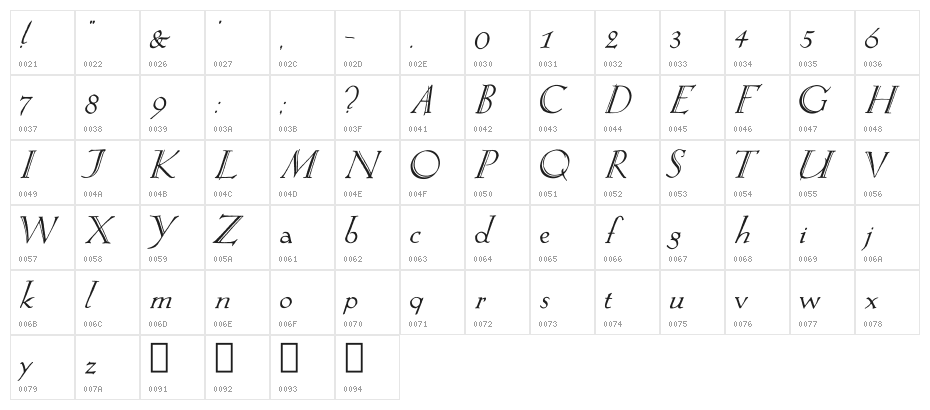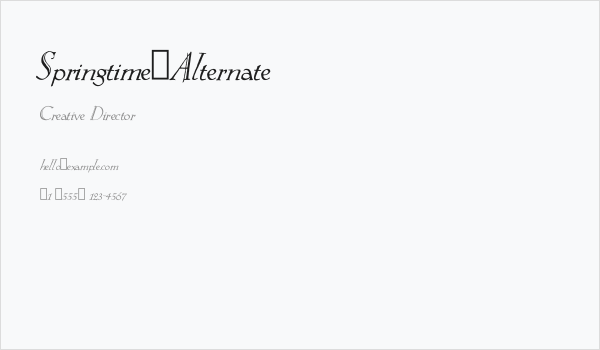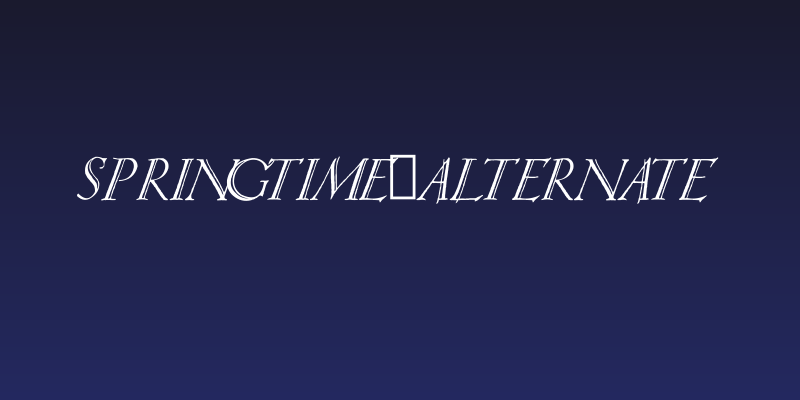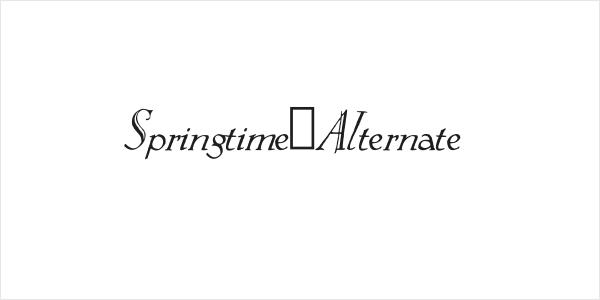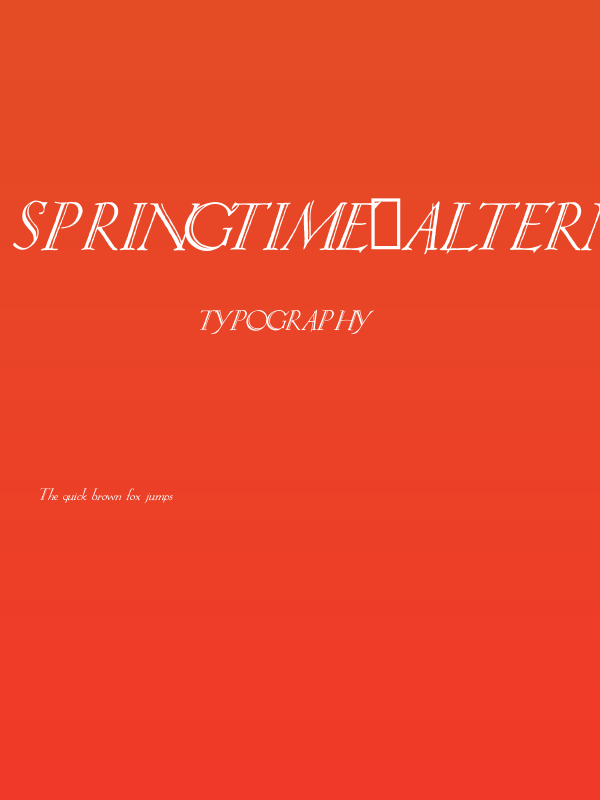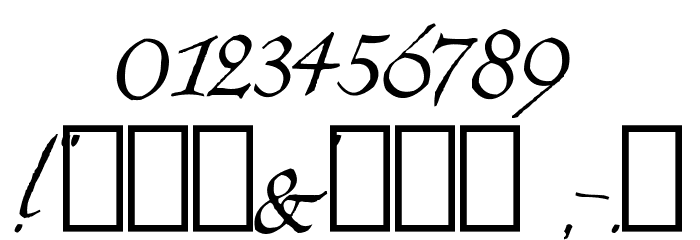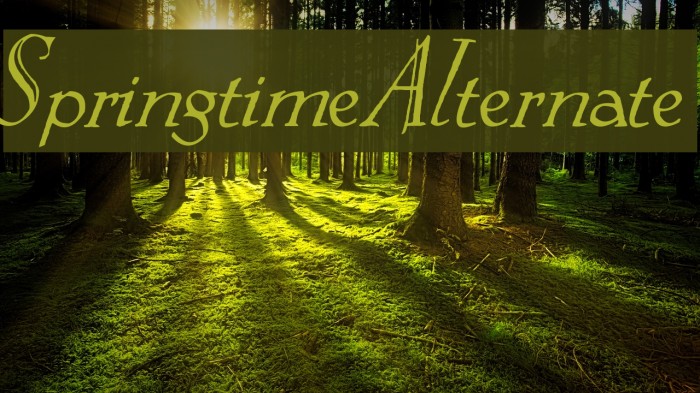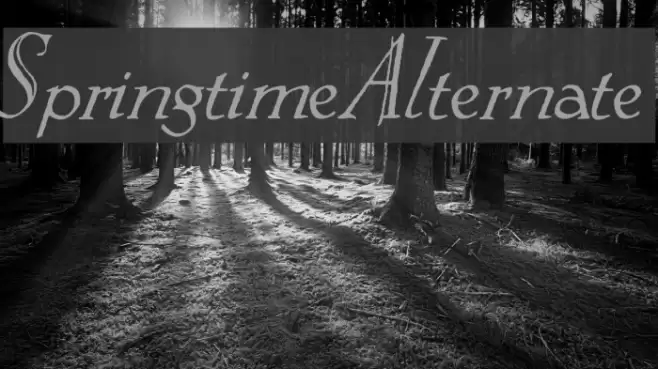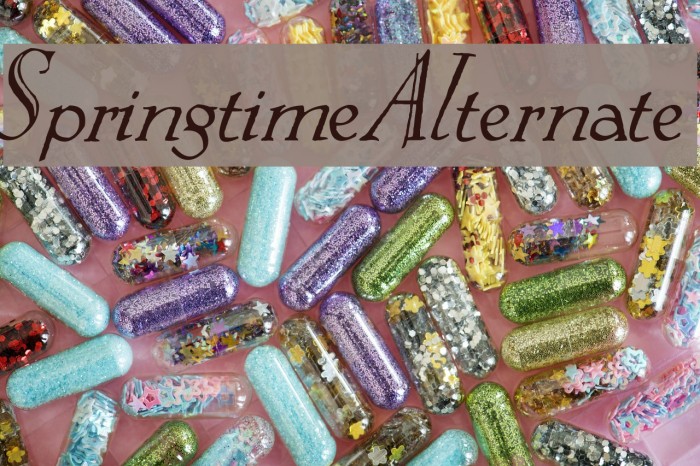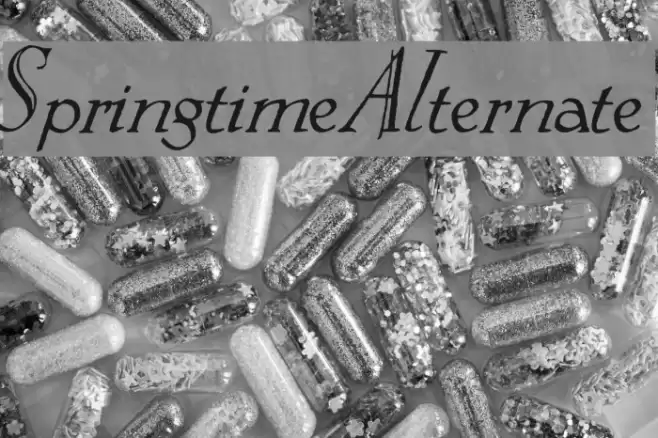
Springtime_Alternate Font
Paul Lloyd Fonts
| 全体的なスタイル | Elegant, Artistic |
| 用途 | Headlines, Invitations, Artistic Projects |
| おすすめプロジェクト | Ideal for wedding invitations, elegant branding, artistic posters, and creative editorial design. |